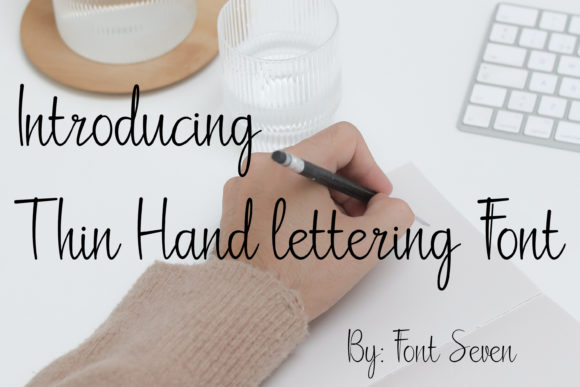
Thin Hand-lettering Script
إذا كنت تبحث عن أصول عالية الجودة مثل Thin Hand-lettering Script، فإن هذه الحزمة المميزة هي خيار رائع لمشاريعك الإبداعية.
تم تصميمه بدقة، ويوفر Thin Hand-lettering Script متجهات نظيفة وطباعة سلسة وترخيصًا تجاريًا لراحة بالك.
سواء كنت تقوم بإنشاء منتجات الطباعة عند الطلب أو دعوات الزفاف أو رسومات وسائل التواصل الاجتماعي، فإن Thin Hand-lettering Script هو الخيار المثالي.